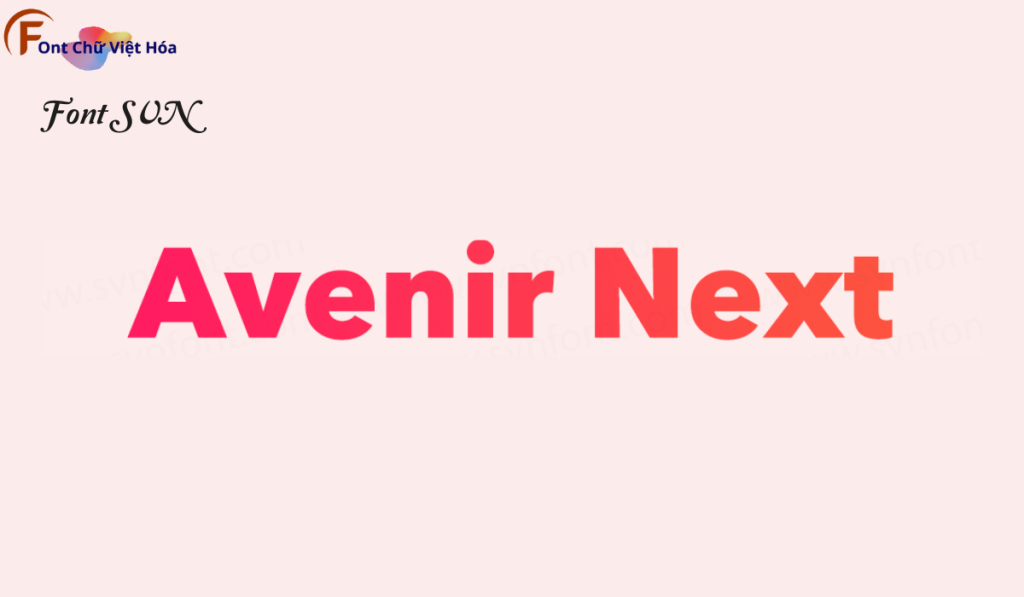
Font SVN Avenir Next Việt Hóa
Phân loại: Đơn giản, Thanh lịch
Độ dày: Mỏng, Thường, Nét đậm
Font SVN Avenir Next Việt Hóa là một font chữ không chân thanh lịch, thuộc bộ font SVN. Được thiết kế với mục tiêu mang lại sự đơn giản và hiện đại, font này lý tưởng cho các dự án thiết kế như website, tài liệu, và bao bì sản phẩm. Với các nét chữ rõ ràng và độ dày đa dạng, Font SVN Avenir Next Việt Hóa không chỉ dễ đọc mà còn tạo cảm giác tinh tế và chuyên nghiệp. Việc Việt hóa font giúp người dùng dễ dàng sử dụng trong các thiết kế tiếng Việt, mang lại sự tiện lợi và thẩm mỹ cao.